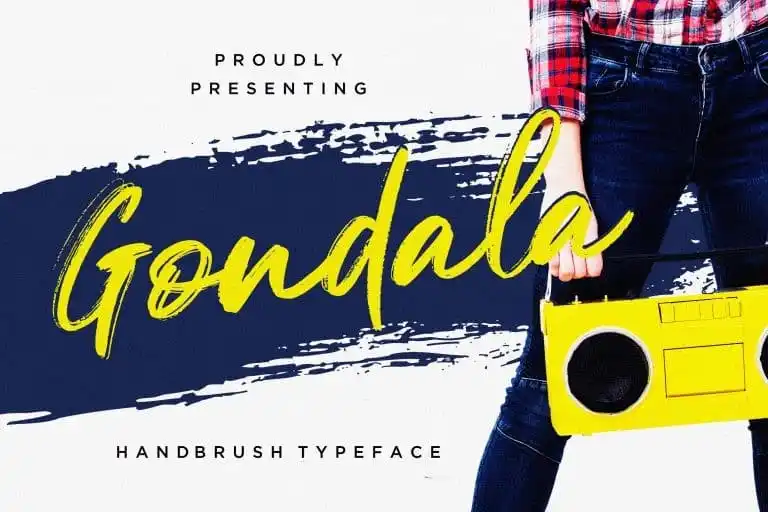
Gondala Brush Font – Download Grátis
A Gondala Brush Font é uma herança delicada criada pela Creatype Studio com estilo de raspagem elegante. Esse belo design manuscrito natural surge com uma textura vibrante que se destaca por sua versatilidade e perfeição para um vasto leque de projetos gráficos, desde a identificação visual até os mais variados tipos de material promocional. Perfeito para criação de marcas, design de casamento, posts no social mídia, anúncios, embalagens de produto, designs de produto, etiquetas, fotografias e marca d’água, além de qualquer projeto que precise de um toque de autenticidade na forma de escrita. Seja para personalizar seu website ou agradar seus clientes através de uma identidade visual única, essa fonte é uma escolha inteligente.